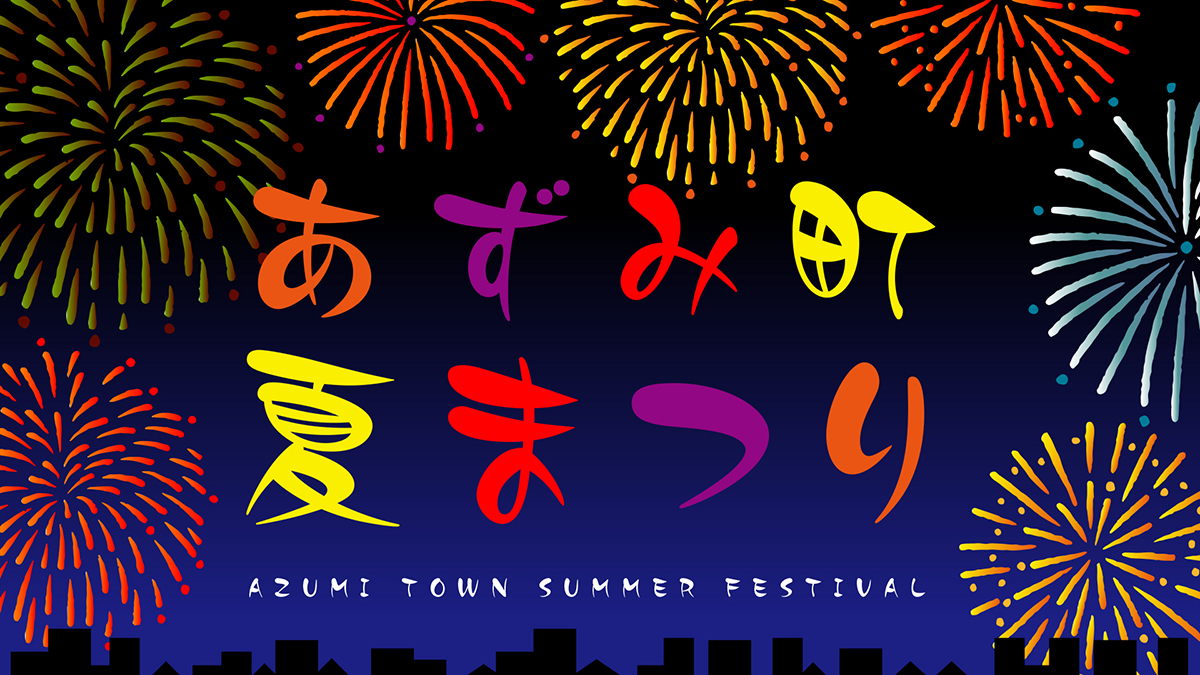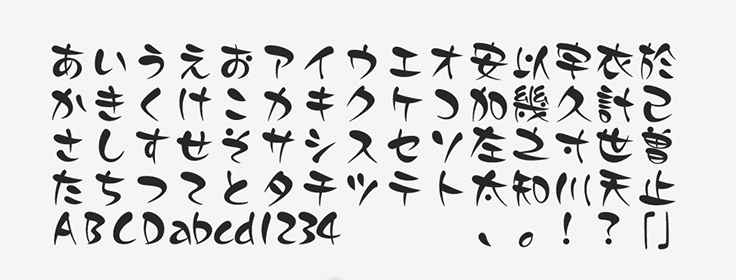
「プリティー桃」について
筆文字と言えば一般的に力強さやフォーマルな印象が強いですが、プリティー桃はそのイメージを一新するようなオリジナルフォントとして開発されました。筆文字系のデザイン書体でありながら、その名の通りにプリティーな愛らしさを備えているフォントです。
「プリティー桃」の特徴
プリティー桃はキャッチコピーなどで活躍するインパクトの強いフォントで、カジュアル感覚で使うことができます。自由でポップな雰囲気が強く、筆で書いたような雰囲気ながらもファッショナブルな表現などにもマッチしやすいことが特徴です。
縦画と横画の太さのコントラストは非常に高く、水彩の平筆で書いたような印象を与えます。ハネやハライの動きも強く、リズミカルな楽しい演出をしたいときに効果を発揮しやすいでしょう。丸い点のアクセントなども楽しく、明るいイメージのフォントです。
フォント名も含めて、1度見たら忘れない唯一無二な面白いフォントです。一定のサイズ以上であれば可読性も高く、見出し・タイトル・キャッチコピーに使いやすいです。作例のように、色文字とも非常にマッチしやすいと思います。